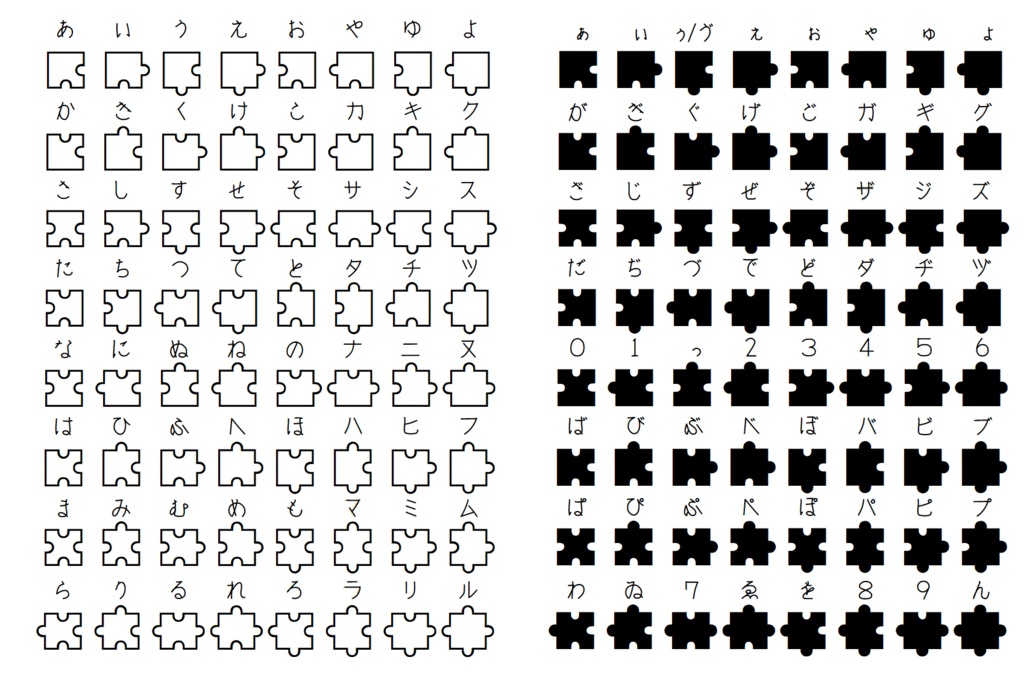
じぐそぉぴぃすそざい(ジグソーピース素材)
ジグソーパズルのピース64×2種に ひらがな、一部カタカナ、数字を割り当て、 暗号文字としてもジグソーパズルの ピース素材としても使えるようにしました。 文字割当表は別画像にまとめてあります。 fontforgeで制作。無料公開、商用可能(自己責任)でお願いします。 ※作りこみが甘かったので微調整しなおしました。
ジグソーパズルのピース64×2種に
ひらがな、一部カタカナ、数字を割り当て、
暗号文字としてもジグソーパズルの
ピース素材としても使えるようにしました。
文字割当表は別画像にまとめてあります。
※作りこみが甘かったので微調整しなおしました。